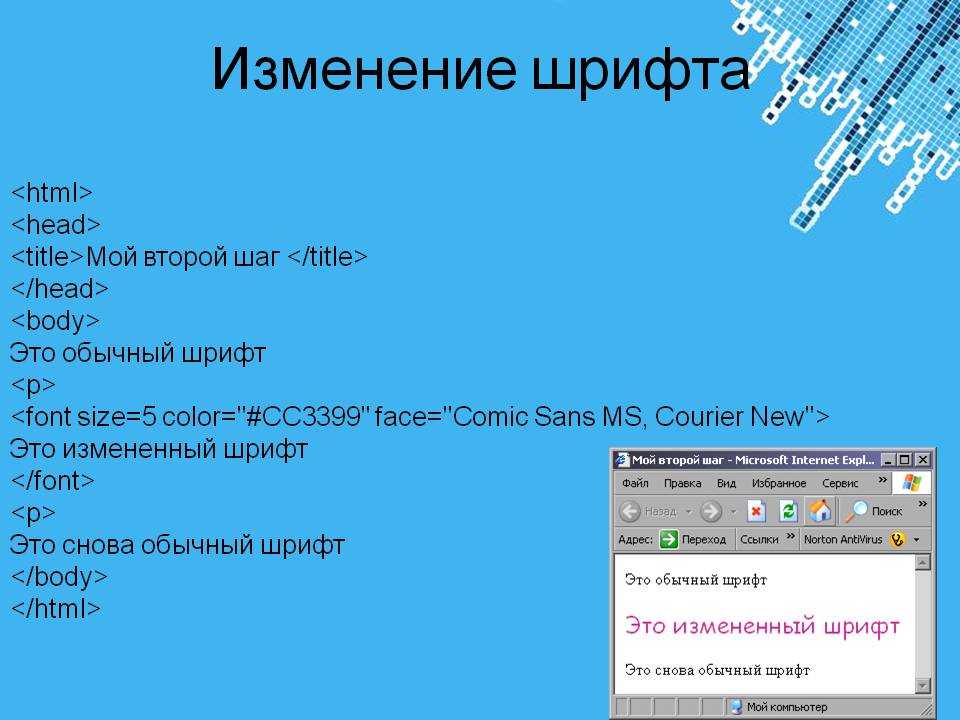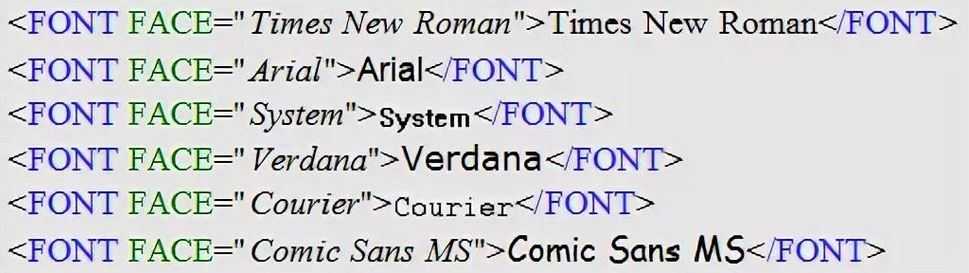
Шрифт в широком смысле слова — это средство
передачи информации (интерфейс, если хотите). В
более узком аспекте — элемент дизайна документа.
Трудно переоценить значение шрифта в оформлении
текста, будь то web-страница, или журнальная
статья. Правильно подобранный красивый шрифт
облегчает восприятие и придает странице свой
неповторимый шарм. Каждый, кто имел дело с
созданием документов на языке HTML для публикации
на Word Wide Web, сталкивается с большим количеством
проблем, связанных с применением шрифтов. Эта
статья посвящена, прежде всего, использованию
шрифтов в Web-дизайне. Однако, проблема оформления
текстовых документов возникла за несколько
тысяч лет до появления Интернета.
В современной полиграфии и дизайне количество разнообразных шрифтов исчисляется тысячами. Условно можно попробовать выделить среди них три стилистические группы:
Кроме того, существуют шрифты для специальных
целей, например, содержащие математические
символы (Simbol), ноты, дорожные знаки, элементы
орнаментов или просто забавные картинки (Webdings).
Но обратимся к главной теме —
применению шрифтов в Web-дизайне. Теги для выделения текста
Если работая с настольной издательской
системой вы можете полностью управлять размером,
местоположением и начертанием текста, то при
создании Web-страницы это невозможно, хотя бы
потому, что вы не знаете, какое экранное
разрешение и средство просмотра использует ваш
читатель. Точный размер шрифта и другие его атрибуты можно задать при помощи каскадных таблиц стилей (CSS). Но о них речь пойдет чуть ниже. Теперь мы подошли к самому веселому
мероприятию — выбору гарнитуры шрифта.Еще пару
лет назад HTML вообще не давал нам такой
возможности: на выбор был пропорциональный шрифт
“по умолчанию” (а это обычно Times) и моноширинный
(Courier). С выходом Netscape Navigator 3.0 часто стал применяться атрибут FACE тега <FONT>. Вместе с этим атрибутом к нам вернулась старая как мир проблема: если какого-то шрифта нет, его нельзя увидеть на экране. Никогда нельзя рассчитывать, что на конкретной машине найдется определенный шрифт. А уж если читатель использует операционную систему, отличную от вашей, то его шансы увидеть задуманный вами шрифт резко падают (особенно, если он использует UNIX). Да, есть такие гарнитуры, которые можно гарантировано встретить практически на любой компьютерной платформе. Две из них я уже упомянул — Times и Courier. Осталось третье семейство — это рубленые шрифты (sans serif). Рубленые шрифты есть в любой операционной системе, но вот называются-то они по-разному: Arial (Windows), Helvetica (UNIX, Macintosh), Geneva (Macintosh). Атрибут FACE позволяет решить эту
проблему, т.к. можно указать сразу несколько
шрифтов: <FONT FACE = “Arial, Helvetica, Geneva”>. Браузер
использует первый слева шрифт, установленный на
компьютере. В данном случае вы можете быть
уверены, что такой тег задействует шрифт
семейства sans serif.
Но не стоит обольщаться — не все так
замечательно. Если вы явно указали имя шрифта для
русского текста, а у пользователя шрифт с этим
именем не содержит русских букв (символов
кириллицы) то он увидит какие угодно иероглифы,
только не русский текст.
Бывают еще более нелепые случаи, когда автор пользуются какой-нибудь программой автоматизированного создания Web-страниц, вроде всенародно любимого FrontPage, которая без спросу вставляет им FONT FACE = «Arial». Затем этот автор переводит текст из CP-1251 (win), например, в KOI8, готовя KOI-вариант страницы. Такая KOI-страница не прочтется, даже если шрифт «Arial» содержит русские буквы — ничего не поможет. Ведь это шрифт кодировки CP-1251, а текст в кодировке KOI8. Никакие шрифты, входящие в поставку Windows95 не содержат русских букв кодировки KOI8.
И все-таки, похоже, решение проблемы
шрифтов существует. Еще в августе 1996 года с
выходом браузера Internet Explorer 3.0 в руках
Web-дизайнеров появился новый мощный инструмент -
каскадные таблицы (карты) стилей (CSS — Cascading Style
Sheets). Таблицы стилей позволяют определить
внешний вид всех элементов Web-страницы, который
сохраняется при переходе от одной страницы к
другой. В файле (.css) или блоке стилей могут содержаться такие параметры шрифта, как размер, гарнитура, толщина, цвет, межстрочный интервал и т.п.
Ну, пожалуй, на этом и остановимся пока. Если гарнитура заголовков в вашем случае имеет
большое значение, то конечно придется прибегнуть
к дедовскому способу — использовать графические
файлы в формате GIF. Что касается использования
графики для передачи основного текста, то это
будет уже явный перебор (хотя, такие сайты в Сети есть). В
любом случае, нужно прислушиваться к чувству
меры. Например, не стоит использовать на одной
странице более трех разных шрифтов — это
указавать абсолютный размер шрифта (лучше
использовать проценты) и конкретные имена
шрифтов (лучше указать семейство). В спецификации
CSS2 предусмотрена возможность встраивать свои
шрифты в HTML-документ, но эта технология еще не
получила широкого распространения.
Однако, объектами авторского
права являютя файлы шрифта, а не собственно
начертания. Никто не запрещает вам нарисовать и
распространять шрифт, названный, скажем, вашем
именем и точь в точь похожий на какой-нибудь Times New
Roman.